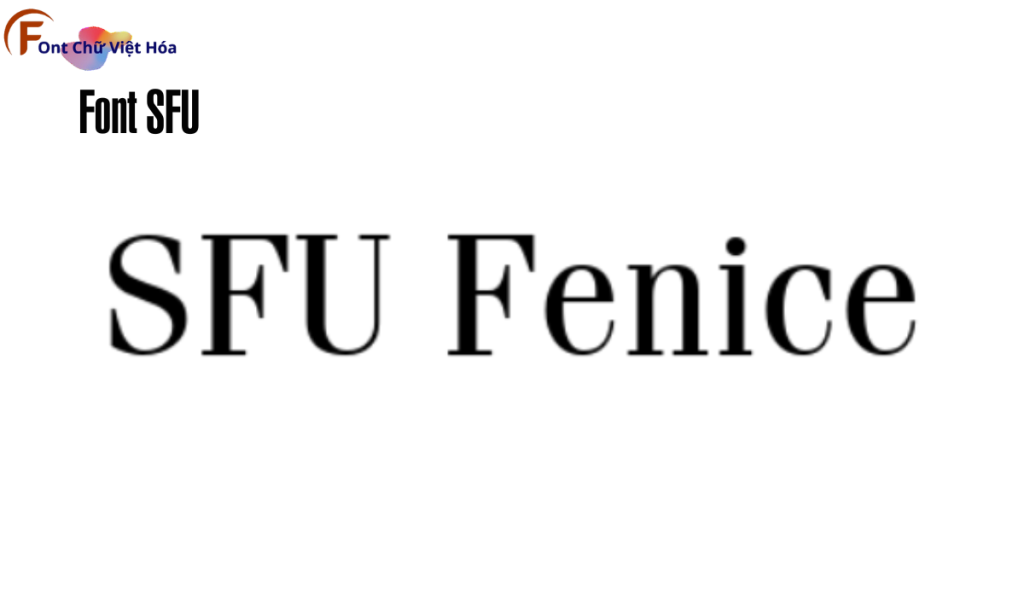
SFU Fenice Font Việt Hóa
Font SFU Fenice Việt Hóa là một font chữ độc đáo, mang phong cách serif hiện đại với các đường nét mạnh mẽ và cá tính, thuộc bộ font SFU. Thiết kế của SFU Fenice tập trung vào sự rõ ràng và dễ đọc, đặc biệt phù hợp cho các thiết kế đòi hỏi tính thẩm mỹ cao như poster, logo, và tiêu đề. Với tỷ lệ chữ cân đối và các đường nét đậm, font này tạo ra ấn tượng thị giác mạnh mẽ và giúp tối ưu hóa không gian trong thiết kế. Font này cũng đã được Việt hóa, mang đến sự linh hoạt và tiện dụng cho các dự án thiết kế bằng tiếng Việt.